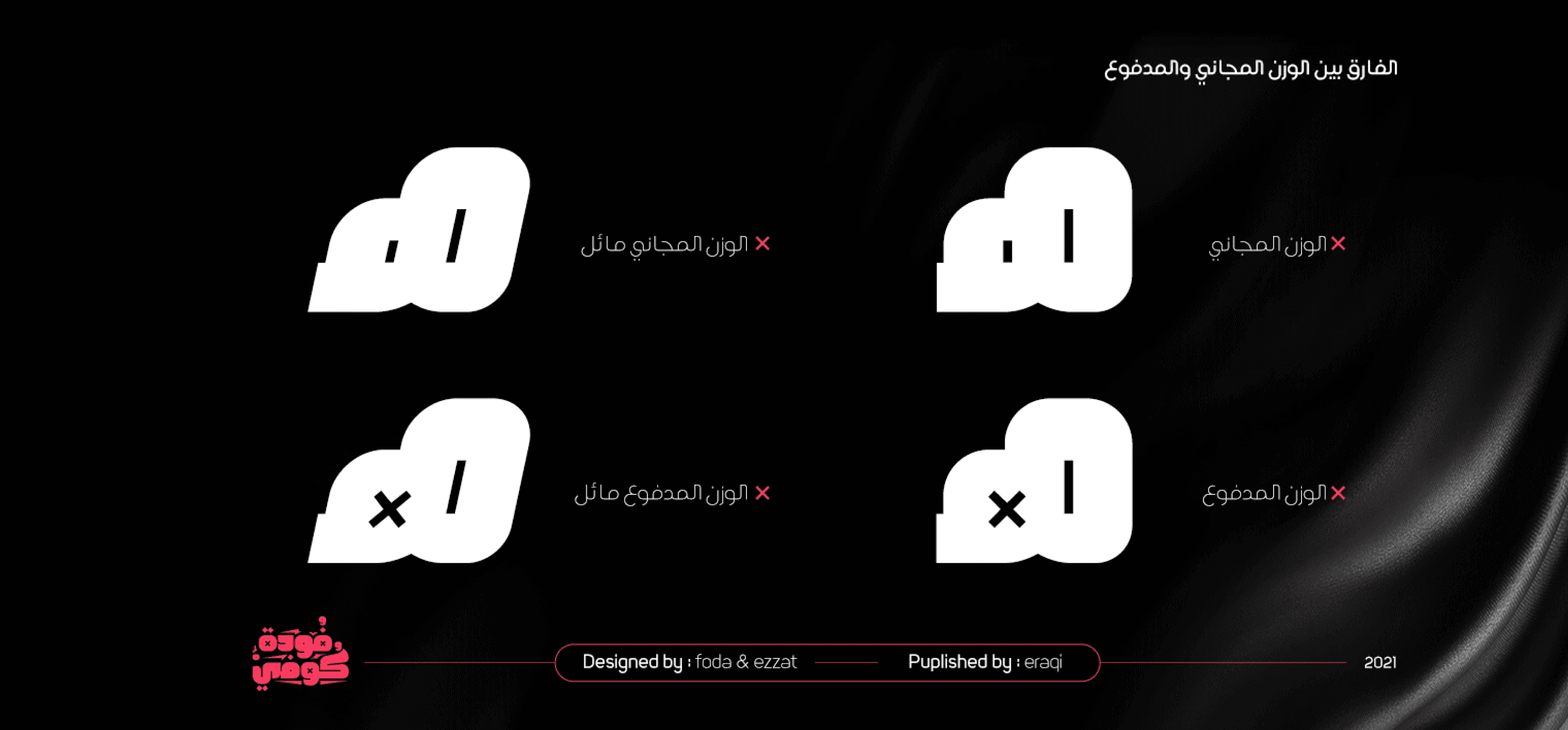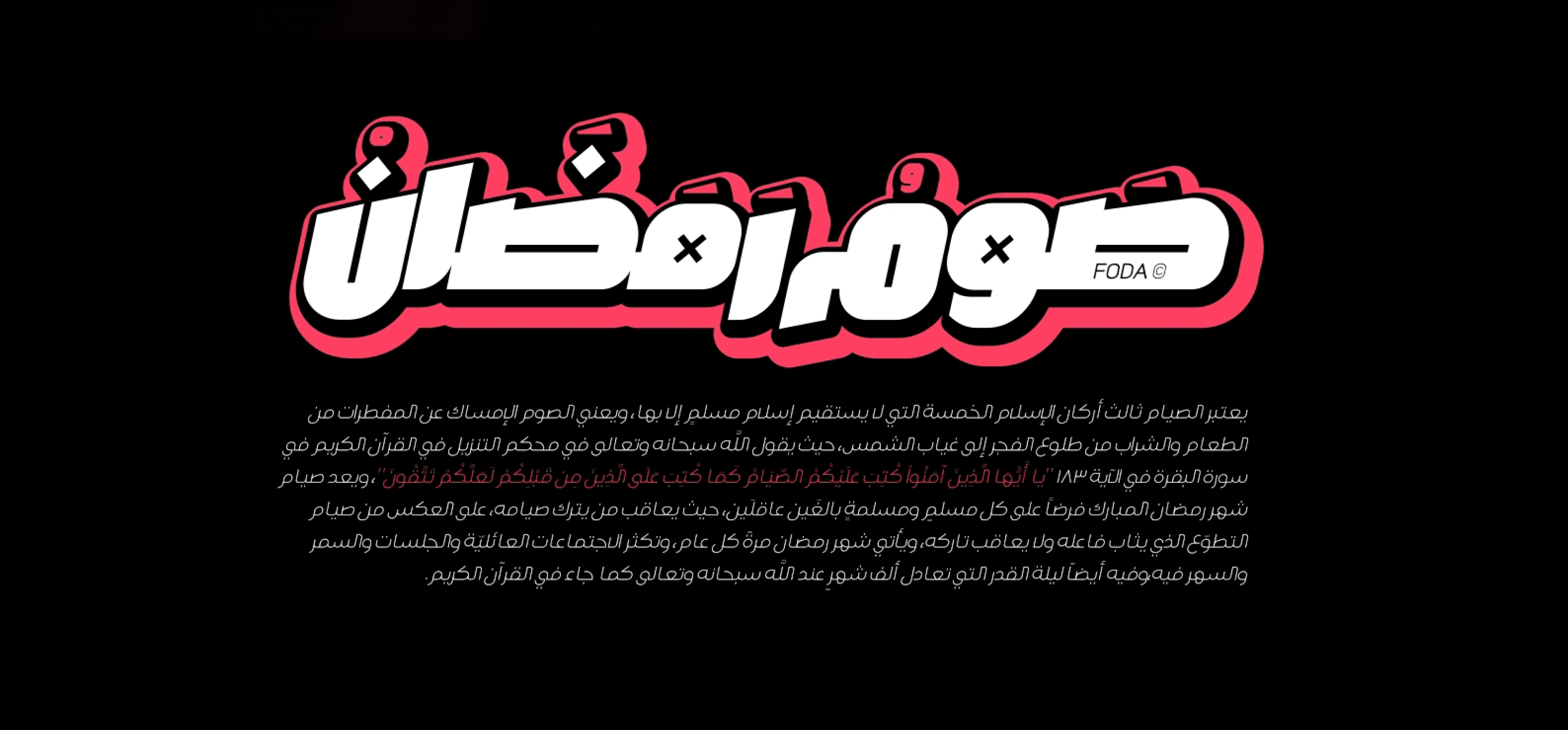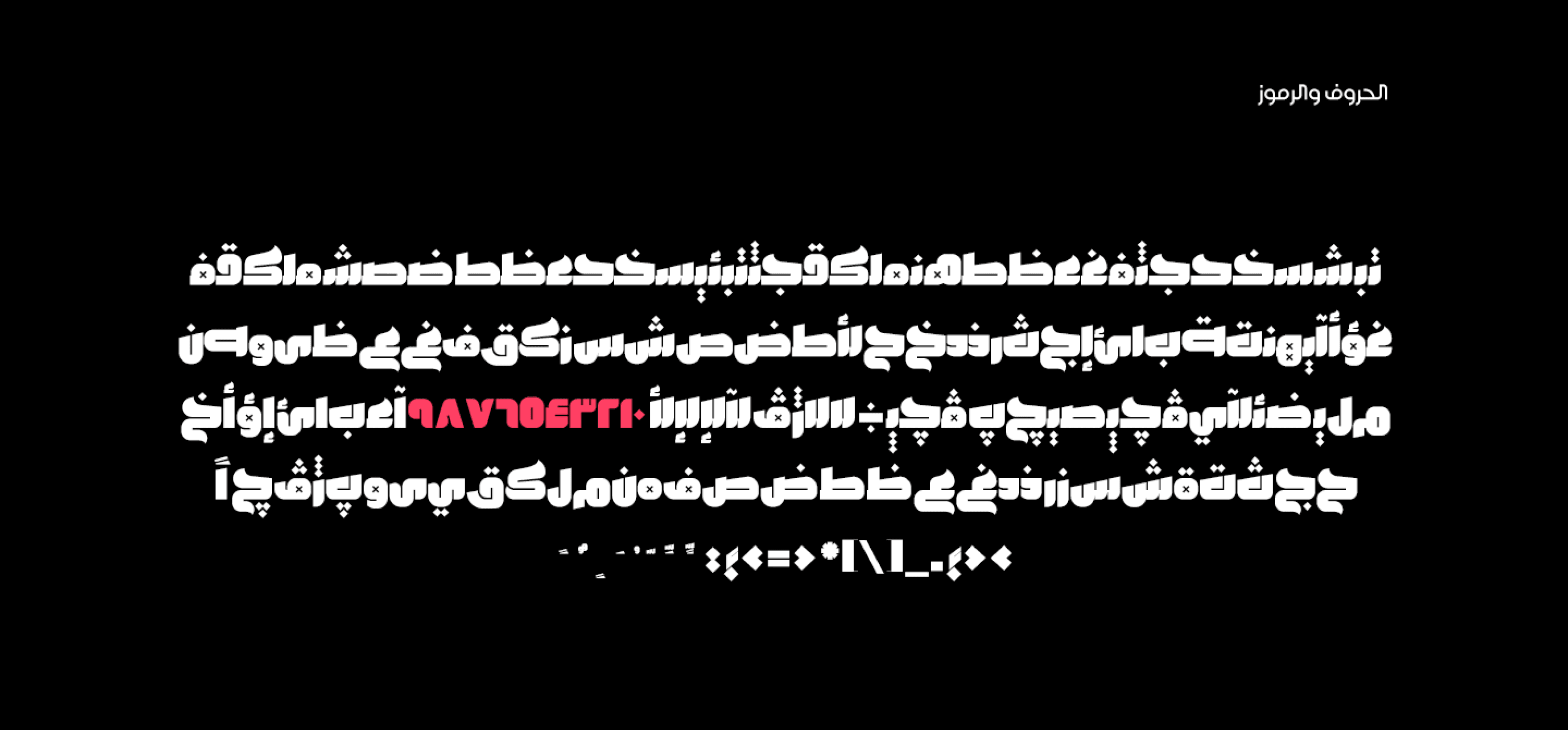
خط Foda Kufi هو خط كوفي عربي عصري يحمل لمسة من الأساليب التاريخية والإسلامية، ويتكون من 6 أوزان: 4 أوزان رئيسية ووزنين إضافيين للزخارف.
يُعتبر Foda Kufi مناسبًا بشكل خاص للعناوين، والكتابات العرضية، والعناوين الرئيسية، والزخارف.